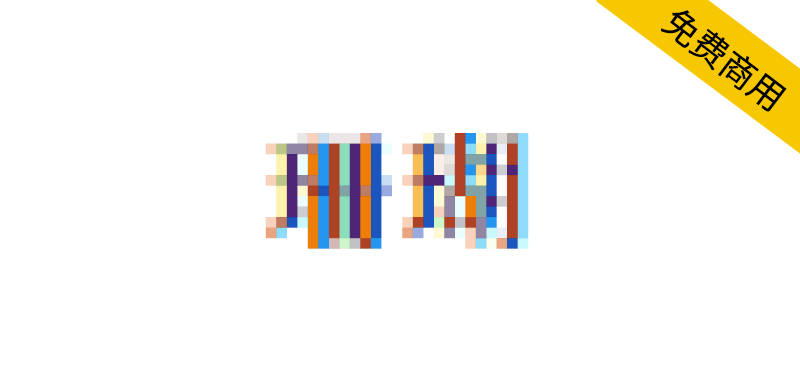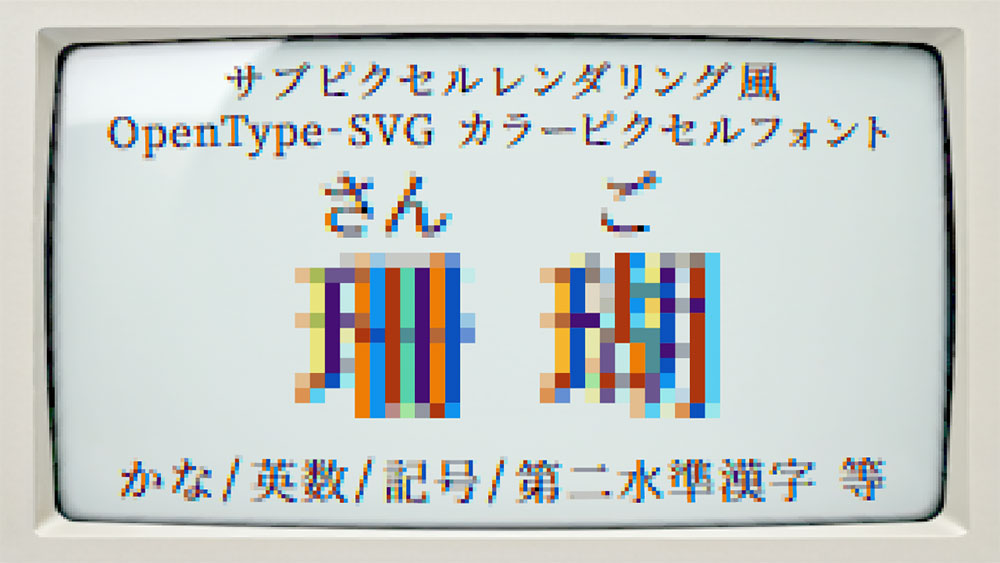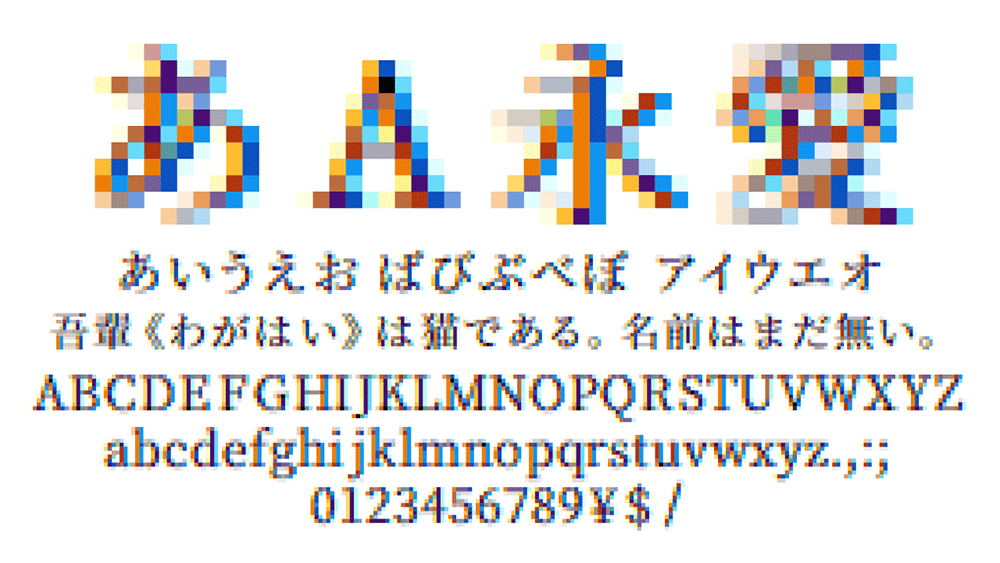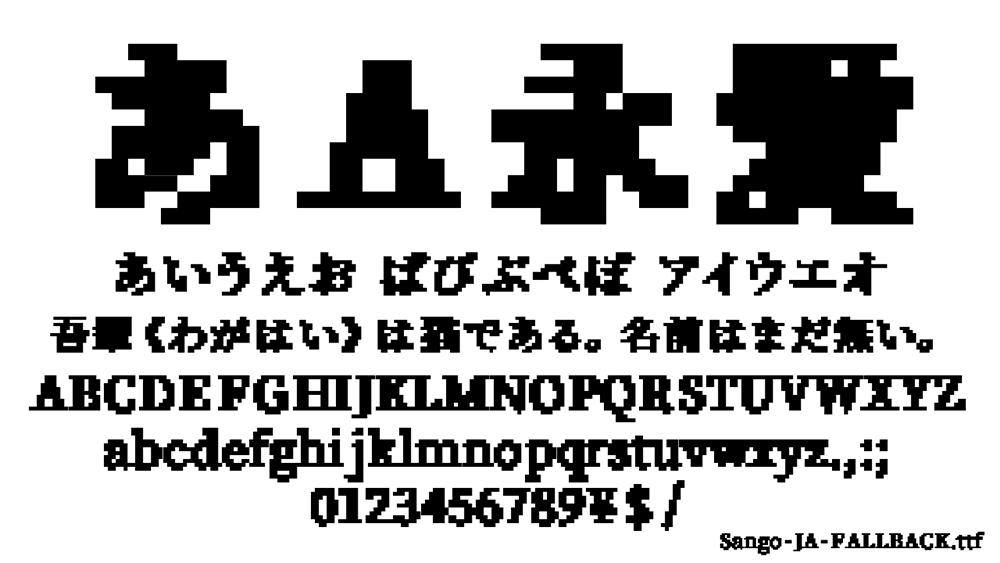
珊瑚(英文名:Sango)是一种参考显示器上的子像素渲染而设计的彩色字体。该字体使用一种称为“像素字体”的样式,由方点组成。像素字体是一种将小方形点组合在一起形成字母的设计。它对于表达复古游戏或强调数字感觉的艺术尤其受欢迎。
“珊瑚”的一大特点是每个像素都添加了颜色信息。这进一步强调了许多像素字体所具有的数字和模拟之间的中间状态,并且根据视角和大小,它们可能看起来有点模糊或感觉像是随机点的集合。
顺便说一句,在“珊瑚”中,彩色部分被设置为透明度,因此如果背景是浅色,则放置时不太可能出现轮廓突出(所谓的边缘)的不自然状态。 (但是,请注意,文本最初是基于黑色文本创建的,因此如果将其放置在深色背景上,颜色可能会下沉并且显示可能无法达到预期效果。如果是这种情况,请使用该应用程序(这可以通过反转侧面的颜色来改善。)
“珊瑚”是一种独特的彩色字体,根据使用方式和排列方式,给人的印象会发生很大变化。我希望您喜欢各种设计!